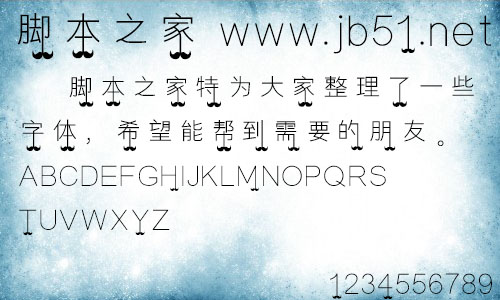
小胡子物語體是一款充滿童趣的中文藝術(shù)字體,正如它的名字所形容的那樣,這款字體中有些一體下方都會點綴一個胡子,看上去煞是可愛,具有很好的視覺感,適合應(yīng)用于藝術(shù)設(shè)計、平面宣傳設(shè)計、網(wǎng)頁設(shè)計等領(lǐng)域。需要的朋友可以前來本站下載。